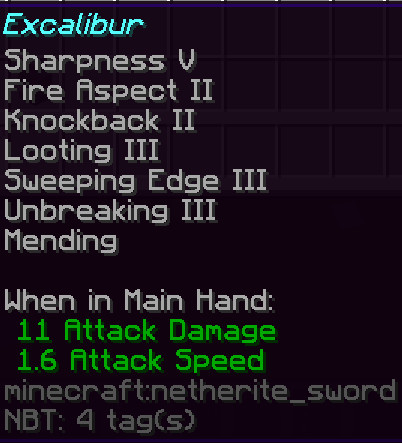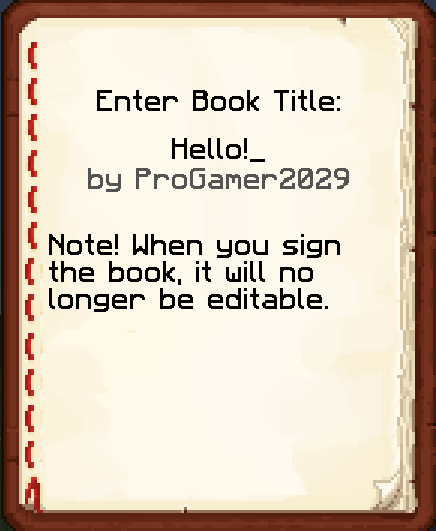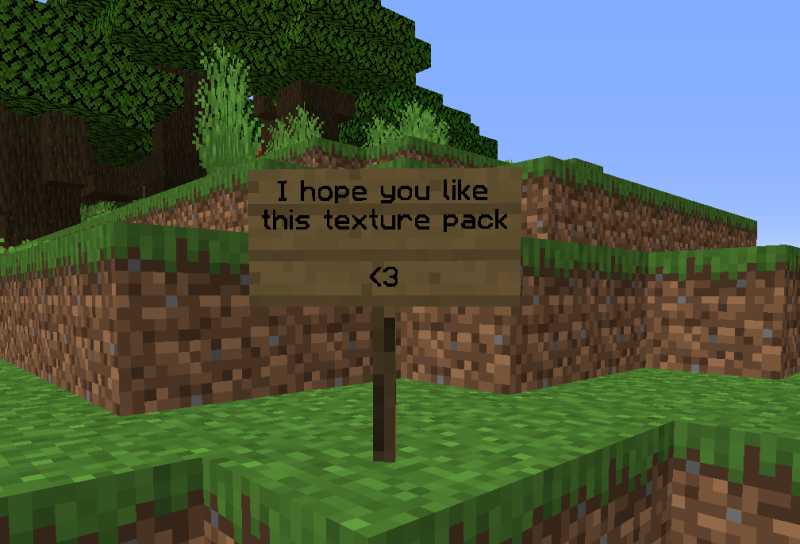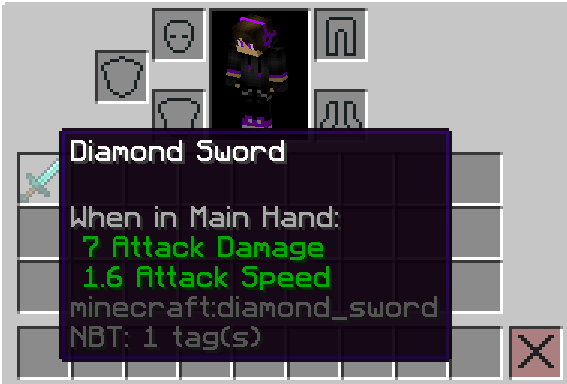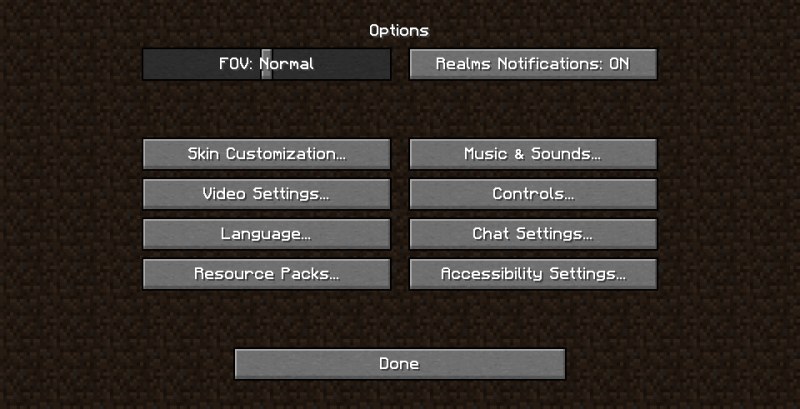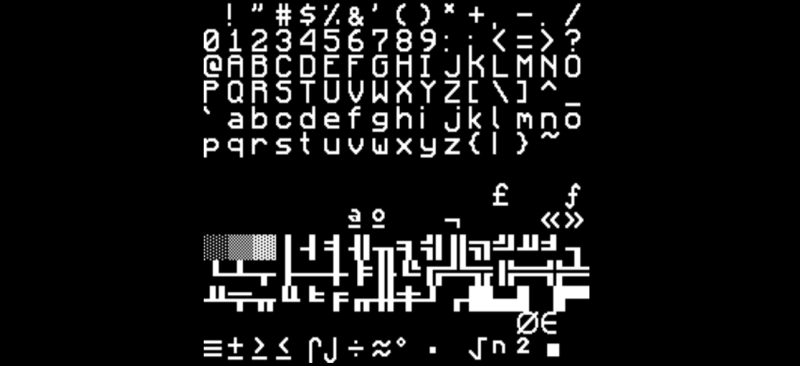
Smooth Font 26.2/1.21.11 (Чистый шрифт, улучшенная читаемость 32x)
Текстурпак Smooth Font - 32x предлагает простое, но эффективное визуальное улучшение для Minecraft, сосредоточенное исключительно на шрифтах. Он заменяет оригинальные текстуры букв, цифр и других символов на более гладкие и отполированные версии, что делает весь текстовый интерфейс игры — от меню до табличек — более чётким и приятным для глаз.
Основанный на популярном текстурпаке Faithful 32x, этот пак сохраняет общий стиль и атмосферу, но сфокусирован на детализации шрифтов. Это идеальное решение для игроков, которые ценят чистый и аккуратный визуал без радикальных изменений в геймплее. Текстурпак совместим с модами и может быть легко интегрирован в любые сборки.
Ключевые особенности:
• Гладкие и чёткие текстуры шрифтов на основе Faithful 32x
• Улучшенная читаемость текста в интерфейсе и мире игры
• Совместимость с модами и поддержка всех версий Minecraft